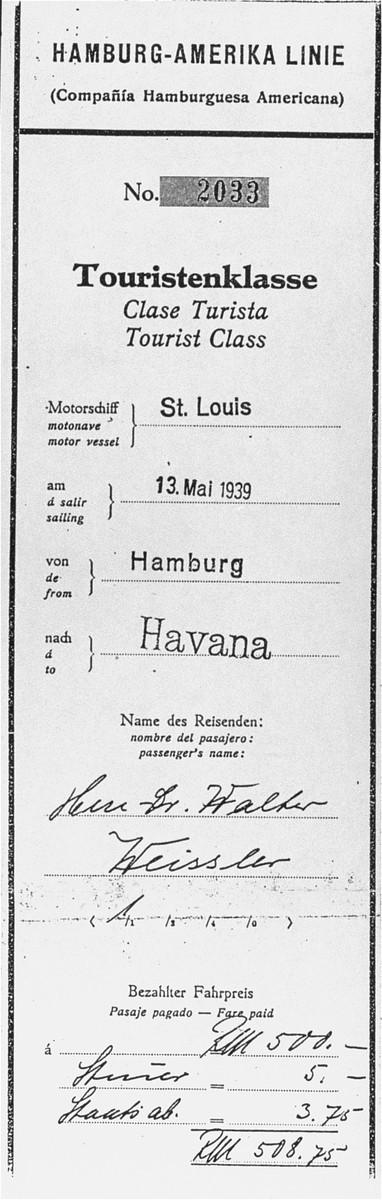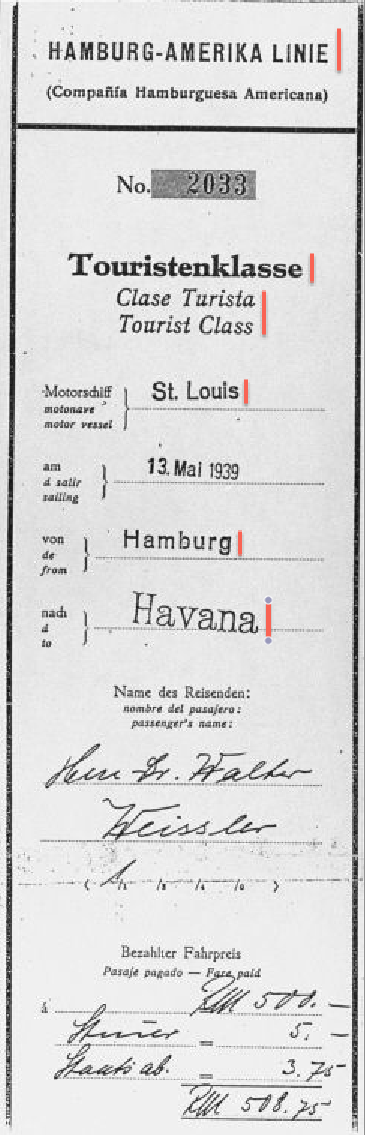
Suche Schriftarten auf dieser Schiffsbordkarte (HAPAG St. Louis) 1930er Jahre
anbei sende ich eine Ansicht einer Bordkarte der Hamburg-Amerika-Linie (HAPAG) aus den 1930er Jahren.
Die gesuchten Schriftarten haben ich rot markiert. Könnt ihr mir bei meiner Recherche helfen und mir sagen wie diese Schriftarten heißen?
Hier noch ein wenig besser aufgelöst:
nur bei "Havana" bin ich noch am knobeln. die schrift erinnert irgendwie an eine typewriter font, aber dann doch nicht ganz ...
trotzdem noch am knobeln, da ich unter deinen genannten begriffen noch nichts passendes gefunden hab...
Ich habe da mal in meine Seemannscanns geschaut, die ich damals für Lars Kähler zugeschnitten hatte, und sich so doch gut durchsuchen lassen:
Das ist beispielhaft die Garamonde von Genzsch & Heyse aus Hamburg